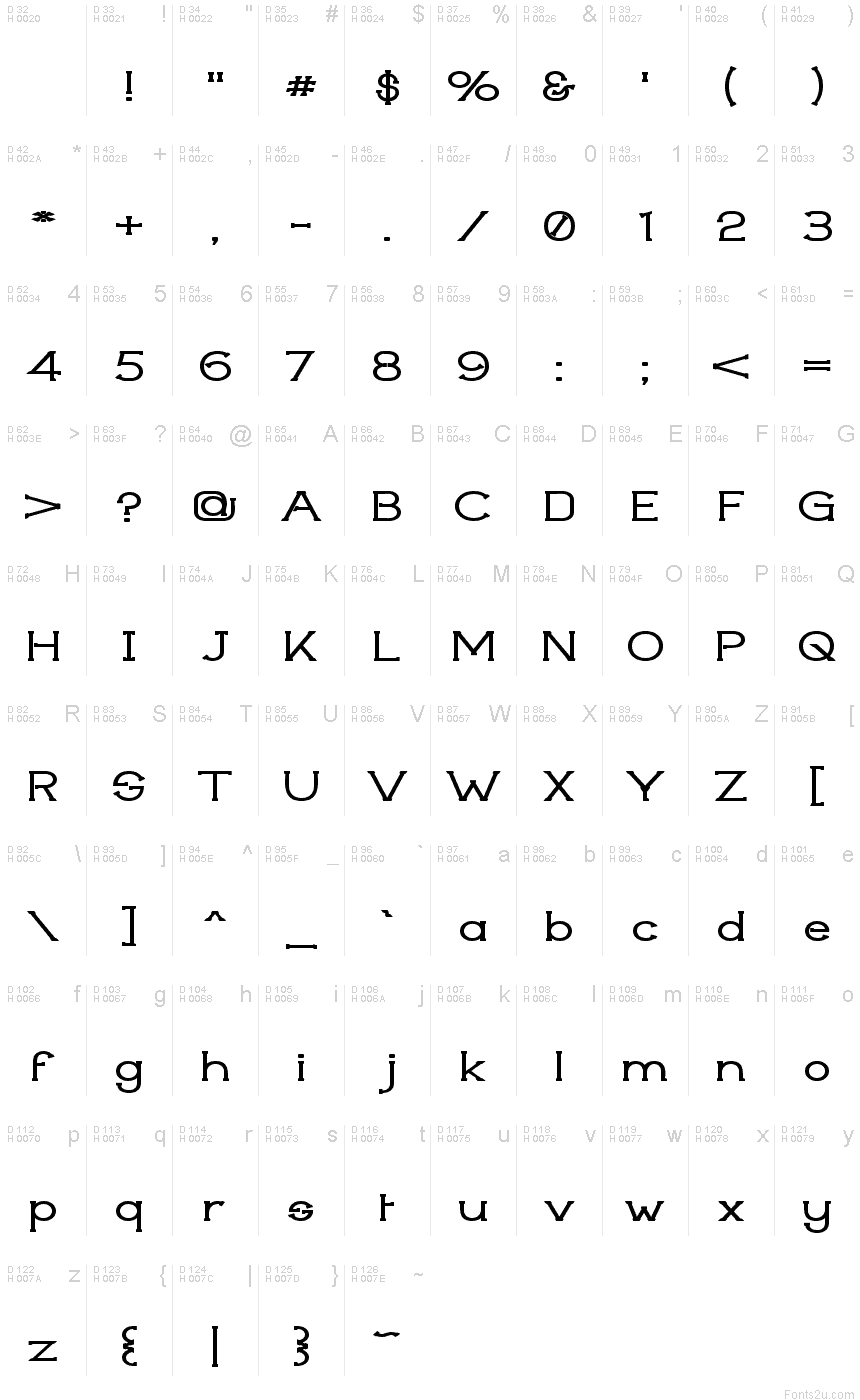
Technically Insane Widesemibold
Technically Insane Widesemibold od GemFonts98 to darmowy, techniczny krój pisma typu display o futurystycznym charakterze. Litery łączą szerokie, zaokrąglone formy z precyzyjnymi łączeniami i drobnymi wcięciami, dzięki czemu całość przypomina połączenie przemysłowej etykiety z zabawnym tytułem z filmu science-fiction.
Idealnie sprawdzi się na plakatach, w grafikach do gier, na okładkach muzycznych, w brandingach aplikacji czy czołówkach – wszędzie tam, gdzie darmowy font ma nadać nowoczesny klimat bez wrażenia chłodu. Szczególnie dobrze wygląda w krótkich nagłówkach lub logotypach, gdzie krągłe kształty i charakterystyczne wycięcia nadają nawet pojedynczym słowom wyrazisty, techniczny rytm.